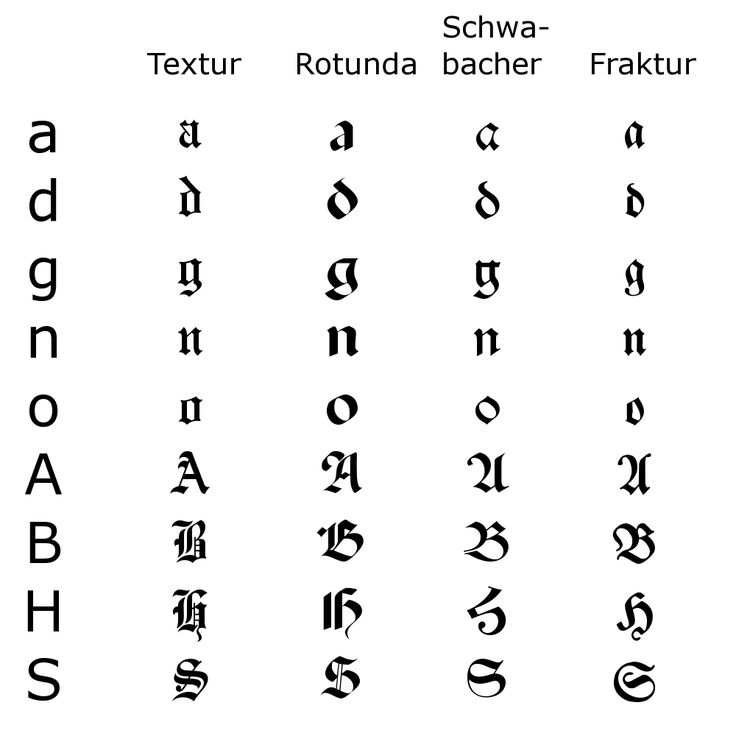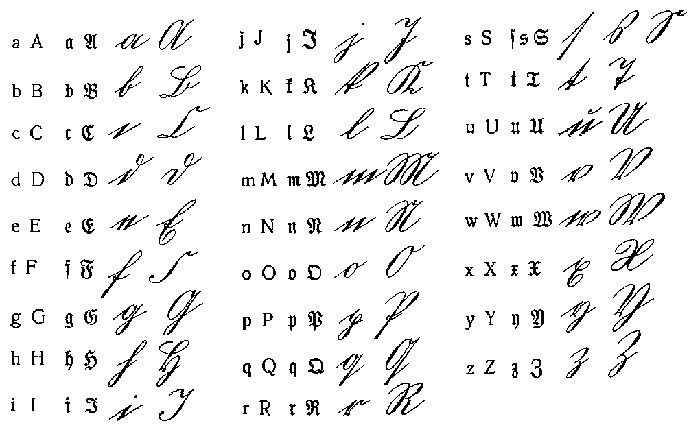
История немецкой письменности и эволюция шрифта
Аннотация. В статье даётся краткая характеристика этапов возникновения и совершенствования немецкой письменности. Кроме того, авторами статьи приводится некоторые типовые начертания готических шрифтов, в последующем оказавшие существенное влияние на становление современной немецкой письменности.
Одним из вариантов представления языка в визуальном оформлении является письменность, которая состоит обычно из совокупности наглядно зафиксированных на какой-либо поверхности знаков. Кроме этого надписи и системы письма могут совмещать в себе, помимо визуальных, некоторые тактильные элементы (например, азбука Брайля). Однако обычно они воспринимаются именно зрительно, а не тактильно.
Учёные-филологи считают письменность одним из самых достоверных свидетельств о языке, точным и естественным источником сведений о нём. Разделяют дописьменный и письменный периоды в истории немецкого языка и немецкой письменности [1 ].
Для описания грамматического строя языка и лексики в дописьменную эпоху исследователи пользуются различными косвенными данными о характере изучаемого языка, а отсутствующий языковой материал восполняют с помощью метода сравнительно-исторического анализа.
В дописьменный период германские племена, расселяющиеся по территории современной Германии, не имели собственного письма.
Они говорили на так называемом прагерманском языке, контактирующем со славянскими и романскими языками соседних племён (финны, балтийские и славянские племена на востоке и севере Европы, древние греки и римляне на юге). Такое тесное взаимодействие (начиная с IV века до н. э.) нашло отражение в некоторых языках в виде германских заимствований.
Рассмотрим подробнее некоторые виды письма, оказавшие существенное влияние на становление современной немецкой письменности.
Руническое письмо. Находки памятников рунического письма германских племён, относящиеся ко II веку, непосредственно связаны с мифологией. Знакам рунического письма, составлявшим первый связный алфавит древних германцев, приписывался магический смысл. Эти знаки являются комбинацией наклонных и вертикальных палочек, линий. Алфавит («старшие руны») содержал 24 знака и по первым шести буквам получил название «футарк».
Происхождение рунического алфавита и в настоящее время не до конца понятно, так как одни руны похожи на буквы греческого алфавита, другие — латинского.
Также высказывались предположения о возникновении рун из италийских алфавитов: возникнув на севере Италии приблизительно во II-III веках, руны переняли самые южные западногерманские племена и постепенно распространили на их север. Однако алфавитный порядок рун до сих пор остается лингвистической загадкой [2].
Руны использовали в основном жрецы в каких-либо культовых и магических целях, их знание было профессиональным секретом. Вырезались руны на камне, дереве, кости, позднее на металле, в том числе на золотых изделиях. Из-за того что деревянные вещи в большинстве своём не сохранились, то и рунических надписей осталось до наших дней крайне мало. К тому же краткость и абсолютная отрывочность рунических надписей стали причиной невозможности адекватной расшифровки значительной их части (около трети). Учёные относят рунические памятники германцев прежде всего к периоду Меровингов (VI—VI I века). Отметим также, что за счёт своего преимущественно культового значения рунические письмена не получили дальнейшего значительного распространения.
Вполне логично, что самобытное применение рунического письма отразилось в лексическом представлении германских языков: например, немецкий глагол «lesen» — «читать», изначально означавший «подбирать» (разбросанные палочки), сохранил данное значение в качестве наименее употребительного наряду с новым «читать», однако предыдущее значение точнее всего сохранилось в некоторых сложных существительных («Weinlese» — «сбор винограда») и в глаголе «auflesen» («подбирать»).
К IX веку наблюдается полное вытеснение рунического письма на территории Франкского государства и постепенная замена его латинским, что становится возможным благодаря процессу часто принудительной христианизации (IV—XII века).
Латинское письмо. Первые упоминания на латинском языке (в большинстве своём имена собственные) возникли у германцев в период, который непосредственно предшествовал появлению письменности на самих германских языках [3]. Наиболее важный с лексической точки зрения материал, записанный на латинском языке, содержат «варварские правды».
Шрифт живет иногда десятки и сотни лет, развиваясь самостоятельно и вместе со всем искусством своего времени. Шрифт необходим людям для передачи информации в письменном виде во времени и пространстве. Письменность является частью общей культуры каждого народа и частью мировой культуры. История возникновения письменности уходит своими корнями в глубокую древность. Сложный и делительный путь претерпел рисунок знаков, прежде чем он превратился в алфавит. Из истории мировой письменности известны четыре вида письма: пиктографическое, идеографическое, слоговое, буквенно-звуковое. Значительно позже, в эпоху образования государств и развития торговли, в Китае и Египте на смену пиктографическому письму пришло идеографическое, письмо при помощи идеограмм, а не букв. Позднее появилось слоговое письмо, в котором знаками обозначались слоги. Слоговым письмо древние египтяне писали на папирусе — писчем материале из стеблей тростника. Первых алфавитов дошло до нашего времени немного. В зависимости от специфики языка в алфавитах разных народов получилось различное количество букв, например, в современном итальянском — 21, в русском — 33, в чешском — 39, в армянском — 39.